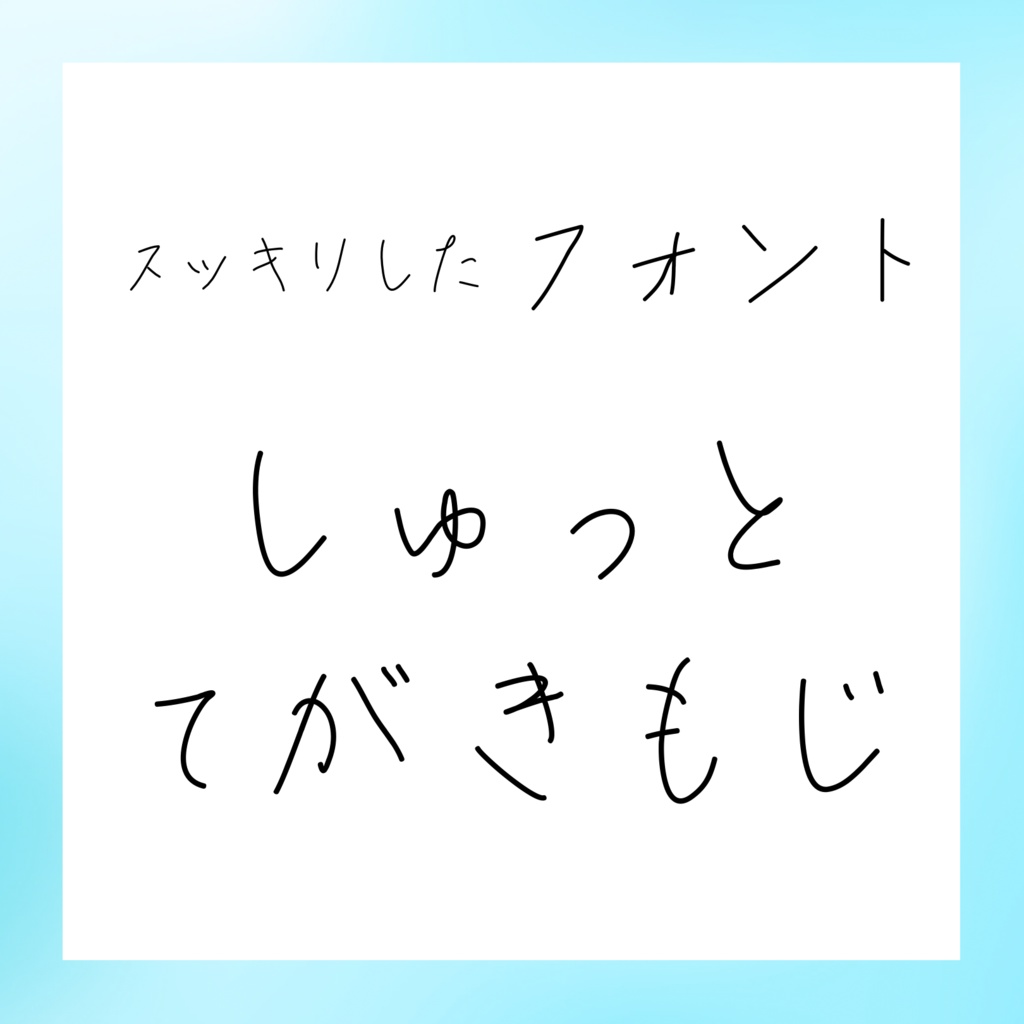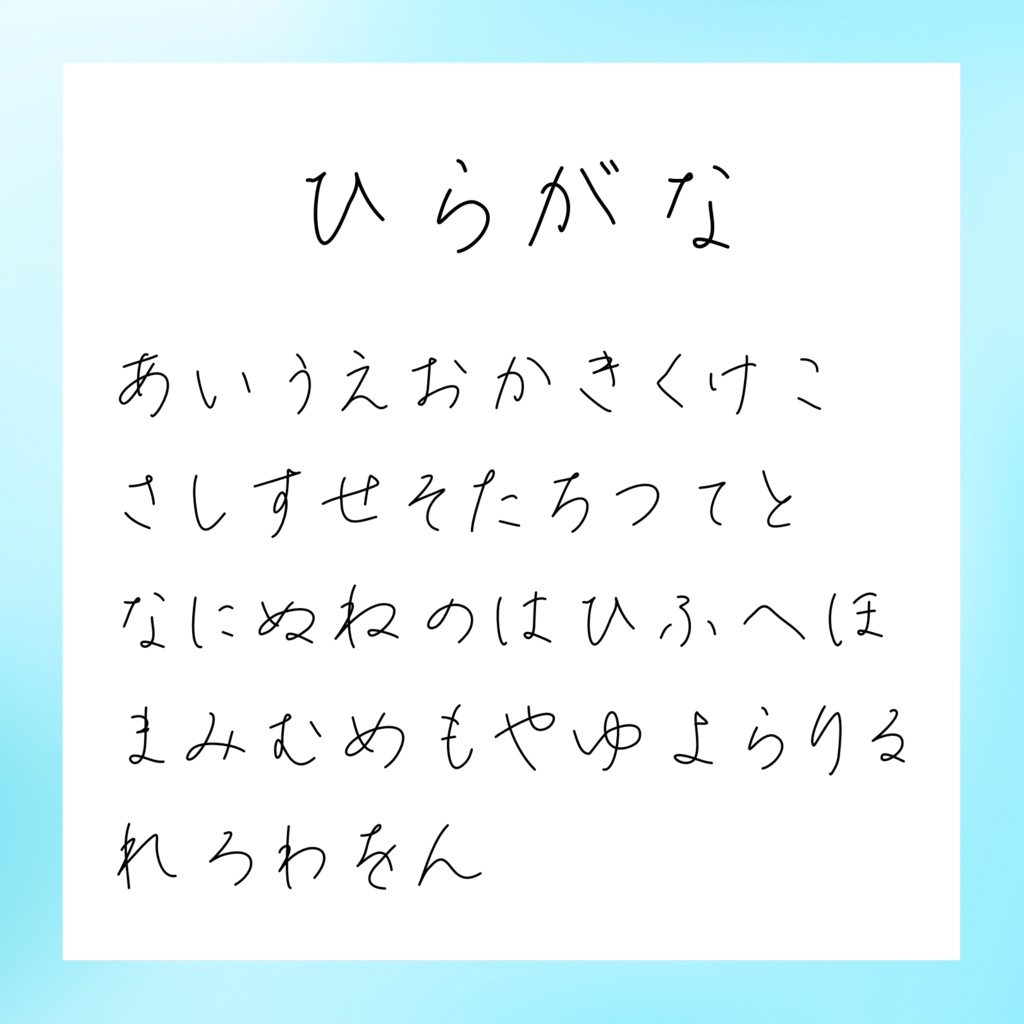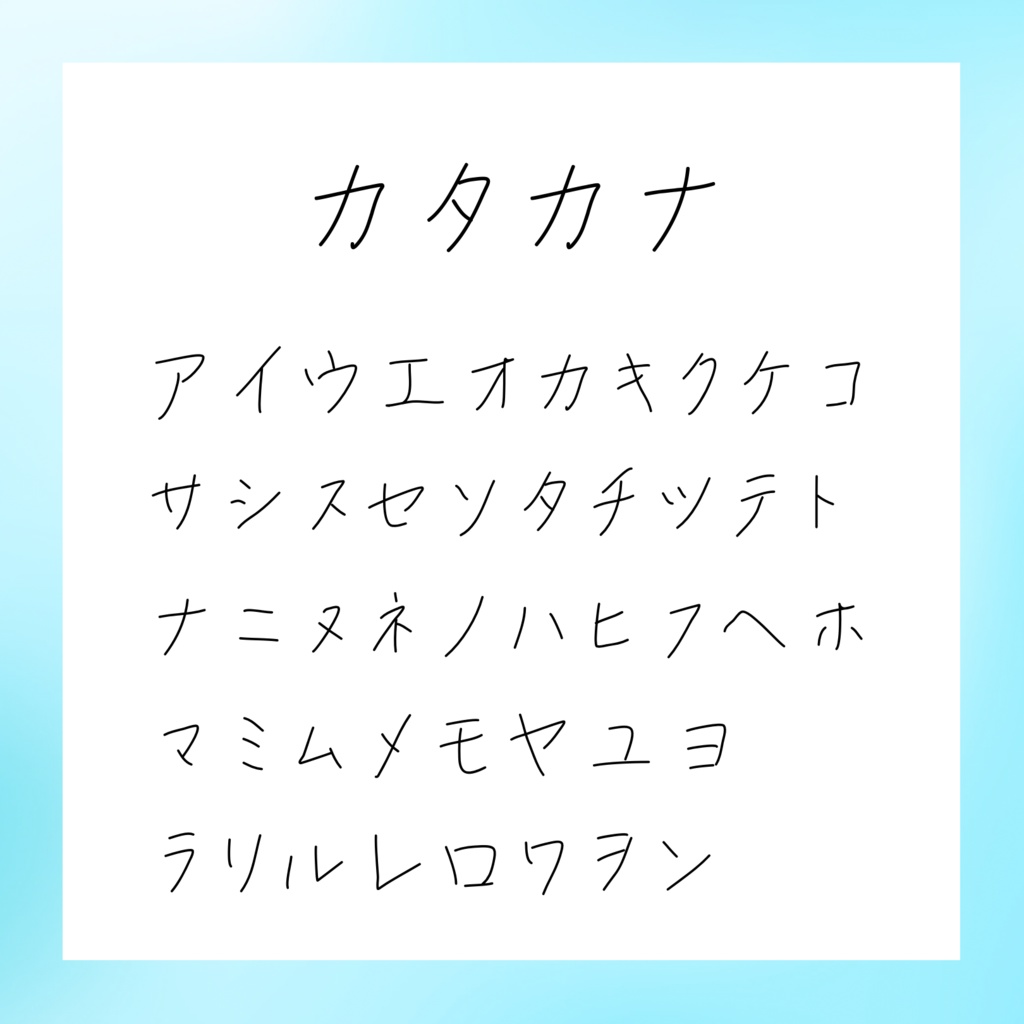
てがきフォント しゅっと
このアイテムについて しゅっとした手書きフォントです。 Webサイト、ポストカード、チラシ、同人誌、動画などでご利用いただけます。 クレジット表記については任意とします。 もちろん、クレジット書いてくれたり、使ったよって教えていただけると励みになります…! 収録文字 ひらがな、カタカナ、英数字、一部の記号 商用利用 ◯ 改変 × 商標登録 × 再配布 × ※ 暴力、成人向け、違法のコンテンツの使用は禁止です。 ※購入いただいたフォントの著作権は放棄しておりません。 ※このフォントを使用することにより、いかなる損害についても責任を負わないものとします。このフォントを使用するにあたり、自己責任において使用することに同意します。 ※この利用規約は予告なしに変更することがあります。利用者は変更された規約に従うことに同意することとします。